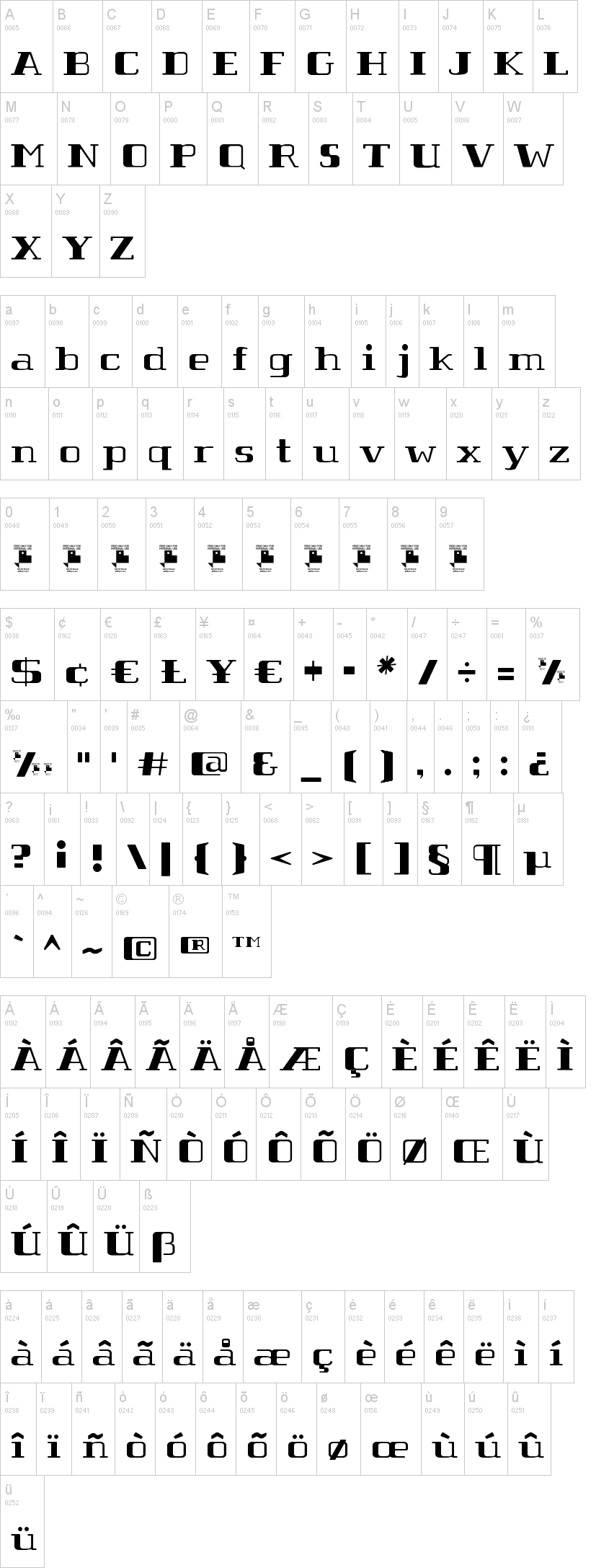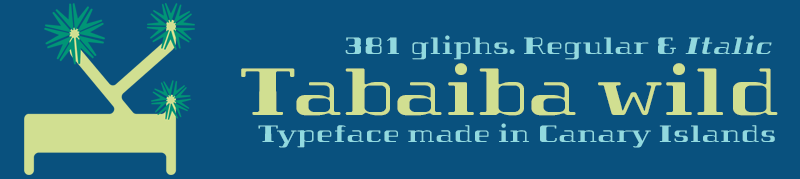
Tabaiba-wild-italic-personal-use.ttfNote of the authorTabaiba wild es mi última fuente hecha antes de irme de las Islas Canarias, es una mezcla de fuente techno y decó con slab serifs redondeados para diseño gráfico
Tabaiba wild is my ultimate font made before leaving the Canary Islands, is a mixture of techno and Deco font with rounded slab serifs for graphic design.